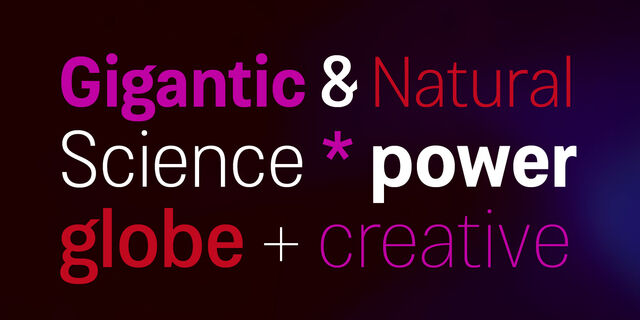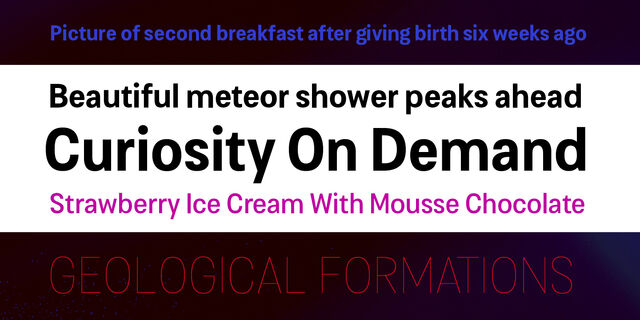
Шрифт Cosima – эффективная рабочая лошадка с оттенком тонкой элегантности. При запуске нового бренда или создании пользовательского интерфейса для мобильных устройств очень важен выбор характерного шрифта. Также для журналов и сайтов типографика всегда является важнейшей частью дизайна.
Срезы штрихов Cosima, расположенные вертикально и горизонтально, делают шрифт прочным и устойчивым. Суженные символы и увеличенная высота строчных букв элегантно влияют на настройки текста и показывают интересные детали в больших размерах.
Это шрифтовое семейство содержит 8 начертаний. Его языковая поддержка охватывает 93 языка на латинице, включая вьетнамский. Он предоставляет расширенный набор дробей, верхних и нижних индексов, строчных и табличных цифр. Подпишитесь на новости и обновления о Cosima на www.anitajuergeleit.de
Шрифт разработала Анита Юргелайт в 2019 году.